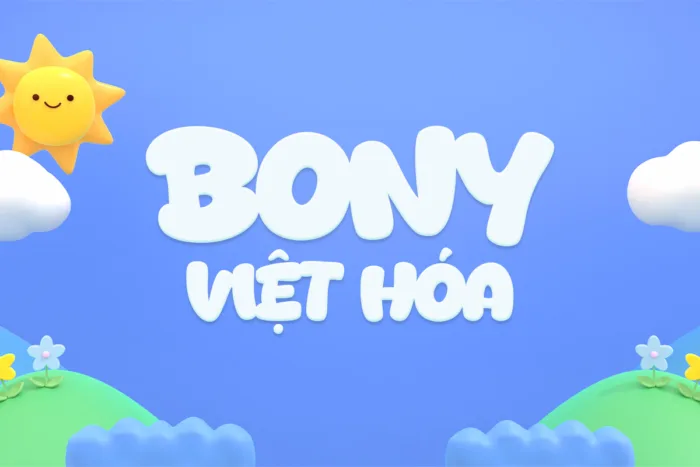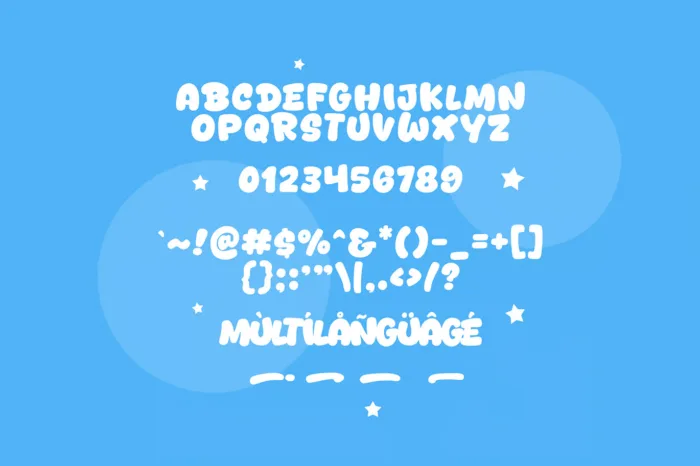
DVN Bony – Font chữ Việt hóa tròn trịa, vui nhộn như bong bóng kẹo ngọt
DVN Bony là một font chữ sans-serif được Việt hóa chỉn chu với phong cách tròn trịa, phồng xốp và cực kỳ dễ thương. Từng ký tự như những chiếc bong bóng kẹo ngọt, mang đến cảm giác vui tươi, năng động và thân thiện. Font không chỉ nổi bật về mặt hình thức mà còn hỗ trợ đầy đủ tiếng Việt có dấu, giúp bạn sử dụng linh hoạt trong các thiết kế dành cho cộng đồng người Việt. DVN Bony đặc biệt phù hợp cho các ấn phẩm trẻ em, tiêu đề hoạt hình, bao bì sản phẩm ngọt ngào hay các thiết kế mạng xã hội đòi hỏi sự bắt mắt và gần gũi. Với khả năng truyền tải cảm xúc tích cực và đáng yêu, DVN Bony là lựa chọn tuyệt vời cho những ai đang tìm kiếm một font Việt hóa vui nhộn, dễ sử dụng và đậm chất riêng.